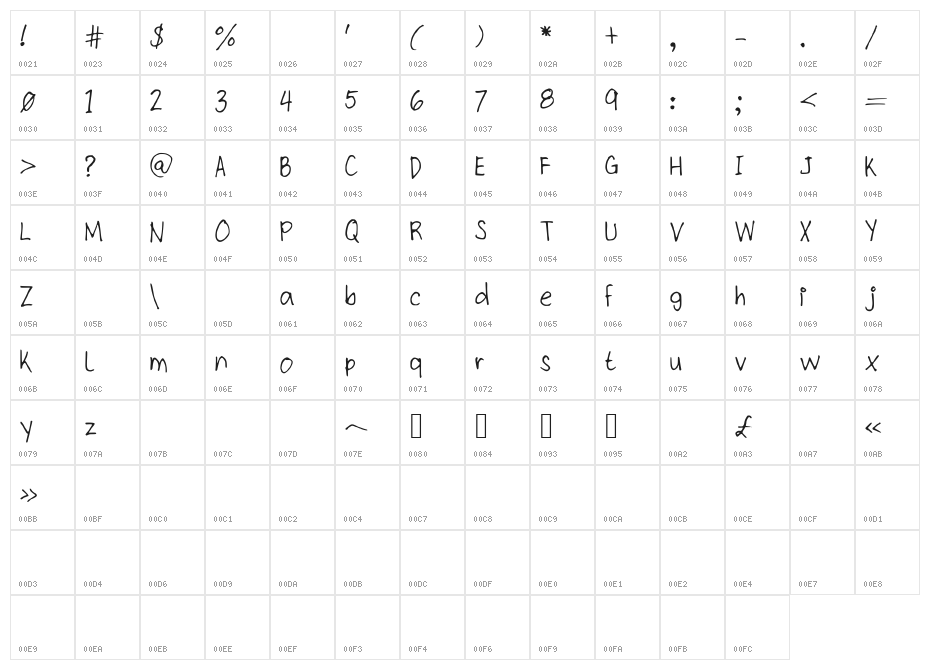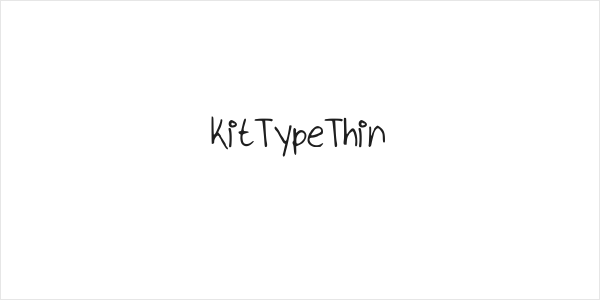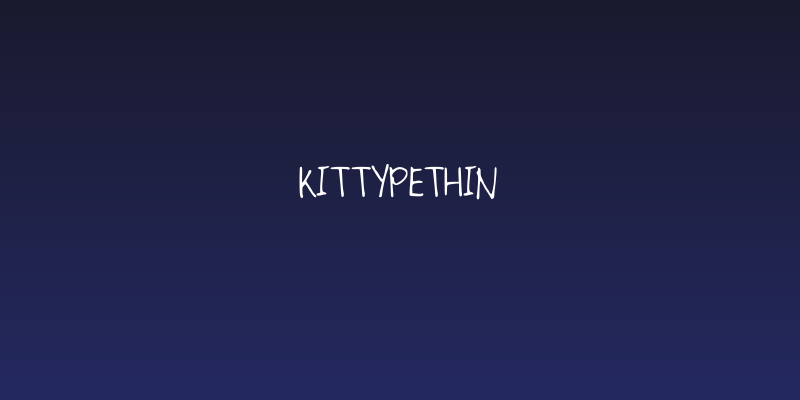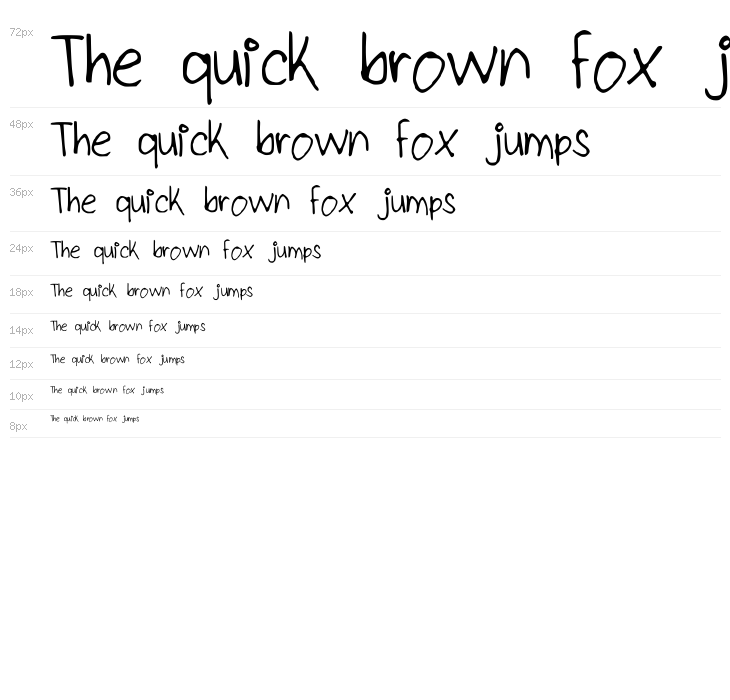
kitTypeThin Font
| Caz de utilizare | Headlines, Informal text, Personal projects |
| Proiecte propuse | Ideal for personal projects, greeting cards, children's books, and informal branding. |